鮮烈な印象の明朝体
紙媒体から動画の編集や電子ブックへとその制作範囲を広げたきっかけのひとつは、山形県庄内でのイタリアンレストラン「アルケッチァーノ」のオーナーシェフ、奥田 政行氏との出会いによるものだといいます。奥田氏は庄内の豊かな食文化を背景に、在来作物を使った料理を提供しています。リブコデザインカンパニーは、庄内の四季に合わせた奥田氏の料理とその食理論を紹介する書籍「食べもの時鑑」のデザインを担当し、電子化の準備もすすめています。
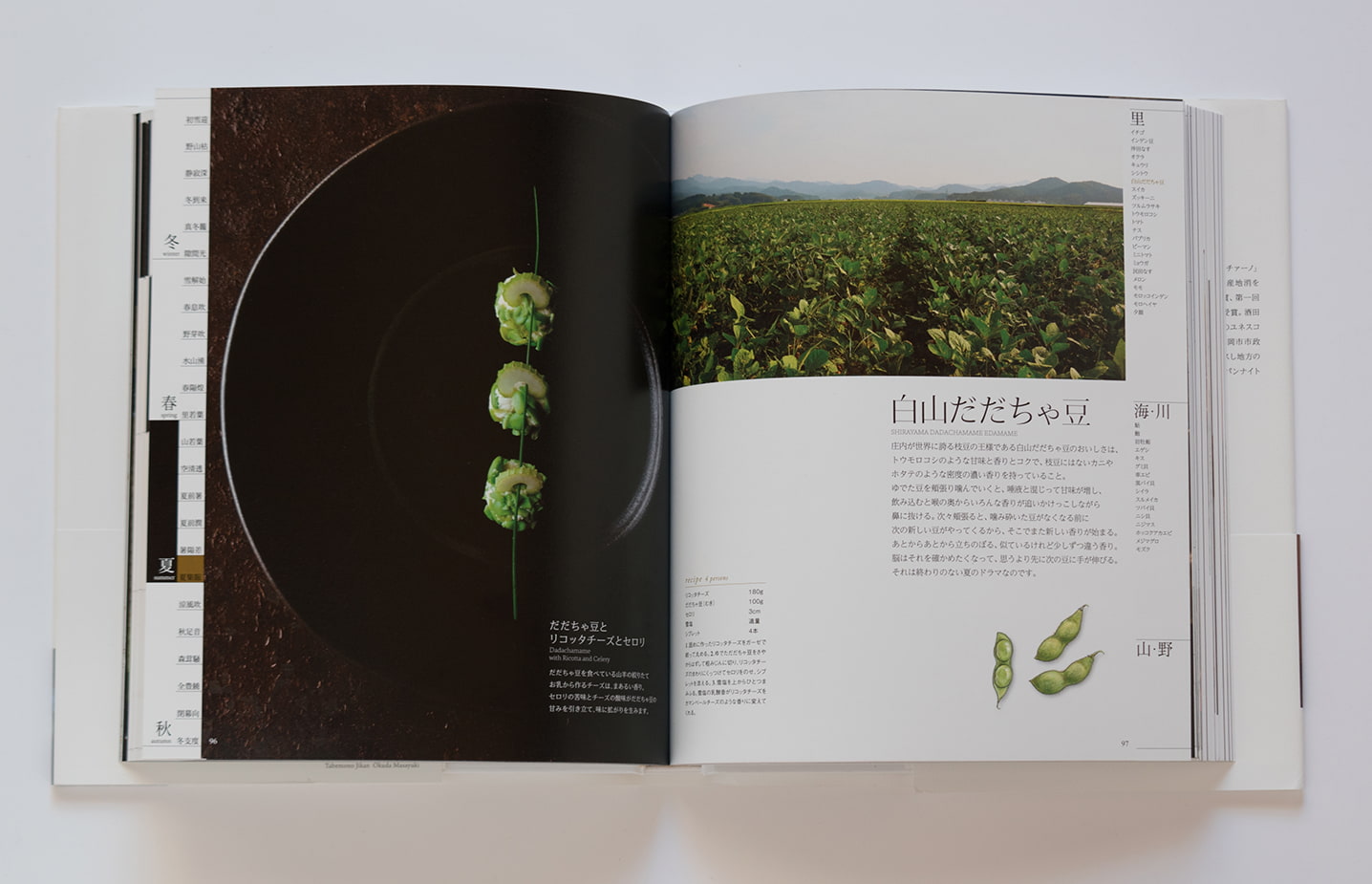
「『食べもの時鑑』の発刊準備編として制作したダイジェスト版で、レイアウトの方針が決まりました。ダイジェスト版は鶴岡市と奥田氏が開催したイベントで配布し、限定的に電子ブックも公開しました。奥田さんは、料理や食に関する膨大なメモを書き留めると同時に、写真家の長谷川 潤氏と共に庄内の四季の写真も撮りためていたので、それらを編集し、1年半ほどかけて本編を制作しました」と、アートディレクターの栗山氏は語ります。
「食べもの時鑑」では、直感的に伝わる庄内の風景写真や、自然をグラフィカルに捉えた印象的な写真を使用しています。デザイナーの原氏は書籍化に際して、この印象的な写真に合う書体は何かと考えたといいます。「奥田さんの『地産地消』という考えは日本的ではありますが、この本の持つメッセージ性を考えると、既存のちょっとオールドなイメージの書体とは違うと思ったのです。『食べもの時鑑』の各節季の扉部分をエモーショナルページと呼んでいるのですが、そこを鮮烈な印象にしたかったのでTP明朝ハイコントラストを使っています。写真の強さに負けませんね。料理名と説明のページは落ち着いた印象にしたいと思い、小さな文字サイズでの可読性を考えてローコントラストにしています」
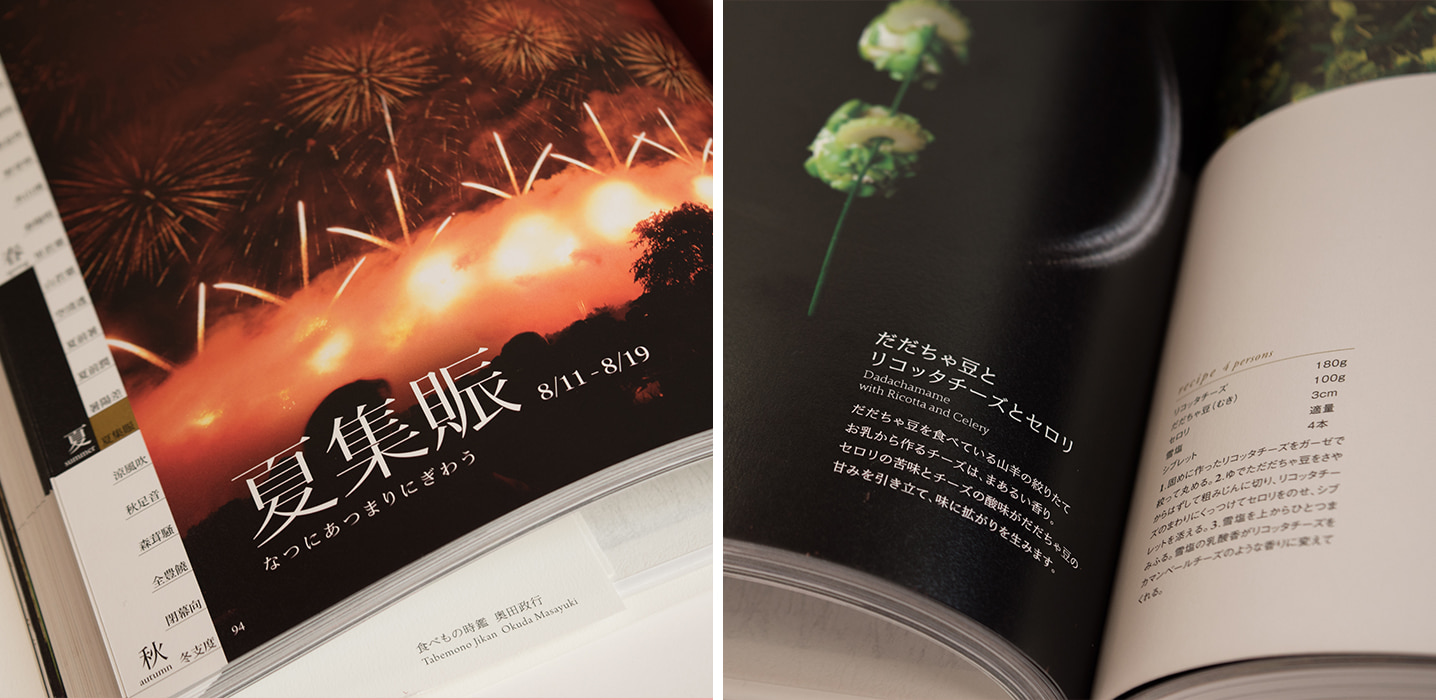
リブコデザインカンパニーでは、オフィス関連事業などを展開するITOKI社や、電気メーカーのカタログ制作も担当しています。制作の際には、クライアント企業へのヒアリングを行い、製品の特性やカタログのコンセプトに合わせた書体選びをしますが、見出し等で他社フォントを選択した場合でも、仕様などの表組み等ではAXIS Fontを多く使用しています。
「表組みの部分は記号や数字が多いのですが、AXIS Fontがあることで安心感があり、ストレスを感じることなくレイアウトができます。書体の選び方によってはスマートにすすまないこともあり、綺麗に組めないことがあります。そんな時は、AXIS Fontを使うと『ビシっと』決まるのでカタログで多用しています。TP明朝とAXIS Fontを組み合せた電気メーカーのカタログでは、TP明朝ハイコントラストとローコントラストを挑戦的に組んでみました。書体は、情報を確実に伝えるものであり、デザインコンセプトに合わせて印象づけるものだと思っています」(原氏)
栗山氏はデザインにとって時代性も重要な要素と捉え、写真の撮り方や書体の選択、レイアウト、紙の素材感などを複合的に組み合わせてカタログや書籍を制作しています。「TP明朝はモダンな印象ですっきりしているので、『さらっ』と使える気がして購入しました。既存の明朝体は、止めやはね、返しにどうしても『匂い』がついている気がするのです。AXIS FontもTP明朝も洗練された書体だからこそ、今の時代を感じる印象づけがしやすいのです」
ウェットで時に古い印象を感じる書体もある中で、TP明朝は、紙でもデジタルでも選びやすいので、メディアが多様化している若いデザイナーの感覚にも合うと思います。